Плиз, подскажите, что за шрифты!
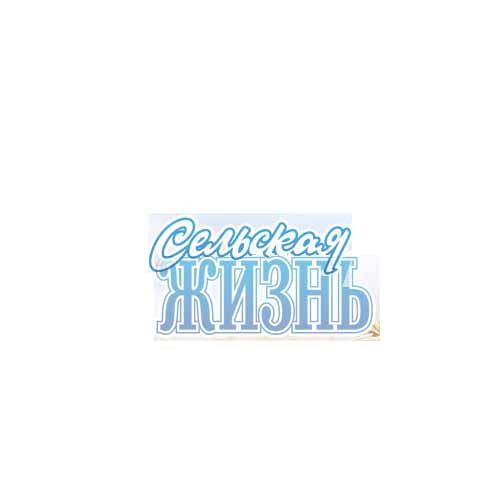
Верхний возможно просто рисованный под лого, а нижний можно получить из какого-нибудь с засечками, полчаса - час работы в векторе и отрисуете один в один, другое дело если хотите писать этими шрифтами что другое, тогда да, надо перелопачивать фонтобазы)
Такое впечатление, что верхний слеплен из латиницы.